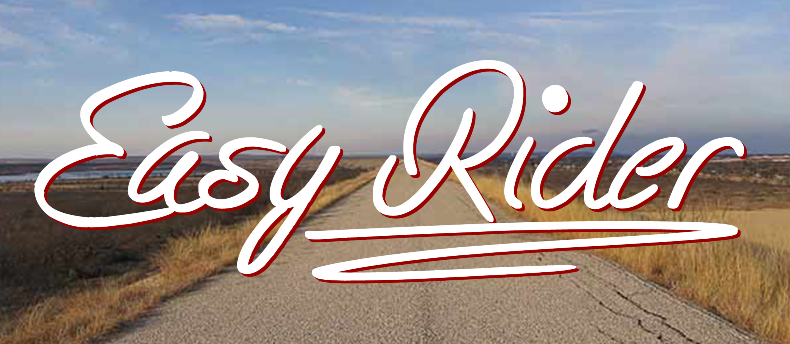
Aqui está uma descrição em português para a página de download da font ‘Easy Rider’, focada na categoria de script fonts criada pelo designer Hamilton: ‘Easy Rider’: Esta font é um texto suave e sofisticado, ideal para criações que exalam elegância. A sua tipografia delicada faz doar-se como uma ótima escolha para design de moda, publicidade ou até mesmo desenhos animados. Com suas curvas sutis e linhas finas, ‘Easy Rider’ é perfeita para produzir um texto atraente que transmite confiança. Seja em letras grandes ou pequenas, esta font irá fazer seu design sofrer uma transformação inebriante. O designer Hamilton criou um script de qualidade com uma certa facilidade na leitura e personalização, tornando-a extremamente versátil para vários tipos de projetos. Com a ‘Easy Rider’, você pode contar com um texto que vai muito além do básico, oferecendo aos seus trabalhos um toque especial. Além disso, o designer Hamilton forneceu informações sobre como adquirir uma licença comercial se quiser incorporar esta font em suas produções comerciais. Visite o site http://www.tattoowoo.com para mais detalhes ou entre em contato diretamente com ele por email no endereço .